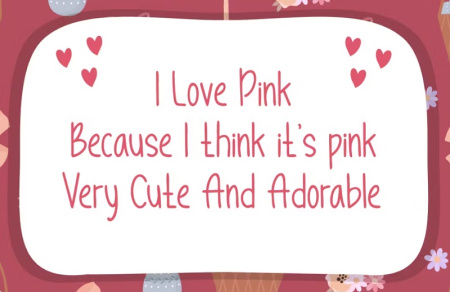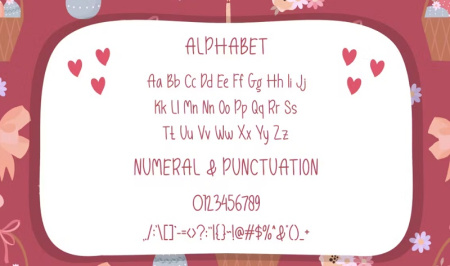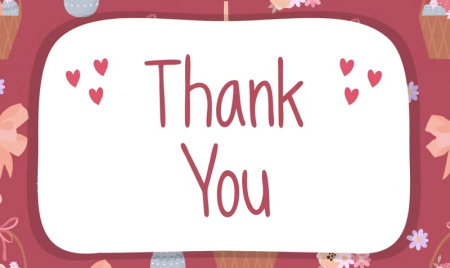
فونت انگلیسی Baimop یک فونت زیبا و ساده که برای همه پروژه ها مناسب است. این فونت انگلیسی با جذابیتی که داره چه در یک پس زمینه شلوغ و چه به عنوان یک عنوان مستقل می توانید مورد استفاده قرار بگیرد! از آن برای طراحی دعوت نامه ها، کارت های تبریک، پوسترها و سایر پروژه های خلاقانه می توانید استفاده کنید.